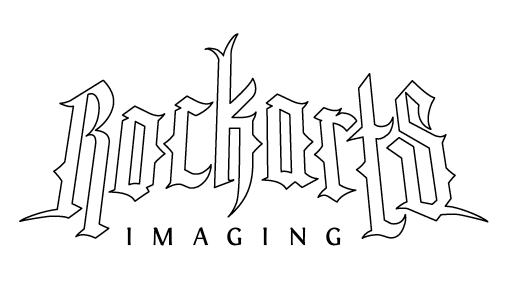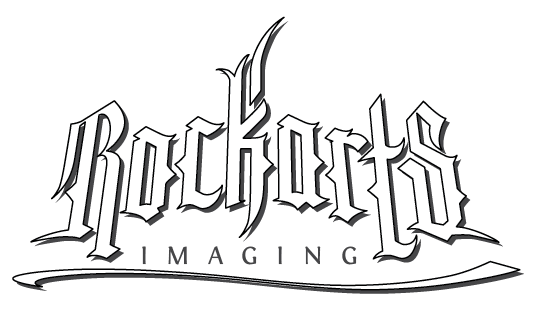
Schriftmischung. Schrift für "Tatoo-Style-Logo" gesucht.
für das angehängte Logo suche ich eine passende Schriftart für das Wort "IMAGING".
Irgendwie macht mich die Sache noch nicht glücklich. Derzeit habe ich die "Fontin" für dieses Wort verwendet. Die Schriftart an und für sich finde ich passend als Kontrast zu dem Tattoo-Style Schriftzug, allerdings bin ich mir mit Größe, Positionierung, Spationierung...völlig uneinig.
Bin für jede Anregung dankbar. Vielleicht schaut Ihr auch mal auf den schnörkeligen Teil. Der Kunde hat das zwar schon abgesegnet, aber ich bin mir beim "tS" noch nicht 100% sicher.
Gefühlsmäßig fliegen die zwei Buchstaben noch so ein bisschen weg.
Also, mir sind zwei Dinge ins Auge gestochen: Einmal scheint mir die unterstreichung vom Stil her gar nicht zum Rest zu passen. Und dann folgendes: Der ganze Schriftzug hat ja Zacken und Ausläufer, und wenn an das so haben möchte, passt es auch ganz gut zusammen; aber am R und am k, diese beiden "losen" Teile... Ich finde die fügen sich irgendwie nicht ein, die sehen viel mehr "Tribal-Style" aus als der ganze Rest. Vielleicht magst Du da noch mal dran schmirgeln ;)
Damit musst Du doch hier rechnen ;)
Im übrigen finde ich dass der Imaging-Teil gut rein passt, von Schrift und Positionierung her und so... Nur zum Kerning kann ich nicht viel sagen, da gibt's hier im Forum Leute die ein viel besseres Auge dafür haben :)
Ok, habs mal umgebaut. Sicherlich geht es irgendwo in Richtung Tribal-Style.
Wie gesagt, mein "Problem" richtet sich allerdings eher auf den Zusatz "IMAGING".
ach so. »Vielleicht schaut Ihr auch mal auf den schnörkeligen Teil« bedeutet also ›bitte keine kommentare zu dem schriftzug‹. bedaure das missverständnis.
Ich persönlich würde den Imaging-Schriftzug nach Möglichkeit etwas kleiner machen und den Buchstabenabstand etwas verringern. Ich denke, dass etwas »gedrungenere« Smallcaps hier besser passen würden. Die Fontin ist meiner Meinung nach auch etwas zu clean. Soll nicht heißen, dass ein Grunge-Font besser passt, aber etwas spezieller könnte es schon sein. Wenn du die die Zacken-Optik aufgreifen möchtest, wäre die Zingha von Xavier Dupré evtl. etwas für dich.
Edit: auch mir sind R und K noch zu glatt.
Ich würd's nicht so filigran machen, auch wenn ich die Fontin eigentlich ganz gern hab. Eher Johnston oder Museo Sans (mindestens Semibold).
Die Sansschrift sollte deine geringste Sorge sein. Die Lesbarkeit des obigen Schriftzuges sollte wesentlich erleichtert werden. Für mich steht da auch »RockorTS« und nicht »Rockarts«. Versuche das a als zweistöckiges einzubinden, dann gibts keine Verwechslungsgefahr. Außerdem ist die Höhe des T und des S unproportional größer als der Rest der Minuskeln. Warum? Sieht unausgewogen aus. Dadurch fallen sie auch aus dem Rahmen.
Und da das T eine Unterlänge hat (!?!) zentriert sich die Subline eher links, was auch unausgewogen aussieht. Lass doch das T oben und nimm als Maßgröße das letzte S. Dann ist die Subline schön in der Mitte.
Die Originalschriftart ist die "SkyClacGothicBB". Bezüglich der Unleserlichkeit habe ich am "o" und am "a" eigentlich garnichts verändert, außer der perspektivischen Verzerrung. Das große "S" dieser Schriftart sieht furchtbar aus, das hab ich selbst gebastelt.
Was die optische Mitte betrifft, wollte ich absichtlich auf das "k" gehen, sonst sieht es echt komisch aus.
Ich weiß nicht ganz, was Du mit dem zweistöckigen "a" meinst!?
Durch die bearbeitet Unterlänge des "R" hab ich nach einem optischen Ausgleich gesucht. Wenn ich das "S" am Ende runterziehe, siehts auch wieder unproportional aus.
Das "S" am Ende soll absichtlich keine Minuskel sein. Kundenwunsch!
Danke für die Anregung, das hilft mir zwar jetzt immer noch nicht mit dem "IMAGING", aber ich bastel mal weiter. :hammer:
Einstöckig:
Zweistöckig:
Danke euch. Man lernt ja immer dazu!
zuerst einlautes Hurrah! Endlich habe ich die Frage und das Problem verstanden.
Zuerst mal zum Zusammenspiel der Schriften: Die Textura wirkt sehr streng, daher wäre es eine Überlegung wert eine ebenfalls strenge ,,Normalschrift'' heranzuziehen. Ich habe im Kopf da immer Schriften wie die Futura oder die Walbaum als Partner für Texturas. Mein Ansatz wäre da eine Futura Heavy (Demibold). Der Unterschied Textura - Serifenlose sollte einen ausreichenden Kontrast liefern können.
Und nun zu den Effekten: Die Textura hat einen 3-D-Effekt verpasst bekommen, die Serifenlose aber nicht. Damit zerfällt das Logo in zwei Segmente (optisch zusammengehörige Flächen). Die Serifenlose sollte also den gleichen 3-D-Effekt verpasst bekommen. Dabei würde aber der Strich unten stören. Der sollte also, wie schon angemerkt, rausfliegen und der Platz für die 3-D-effektierte Serifenlose herhalten. Und der Schriftzug mit der Serifenlosen kann dann gleich den Job des Strichs übernehmen. Alternativ könnte man den 3-D-Effekt auch komplett weglassen.
Vielleicht hast Du zu viel oder den falschen Kontrast im Logo zwischen den beiden Segmenten?